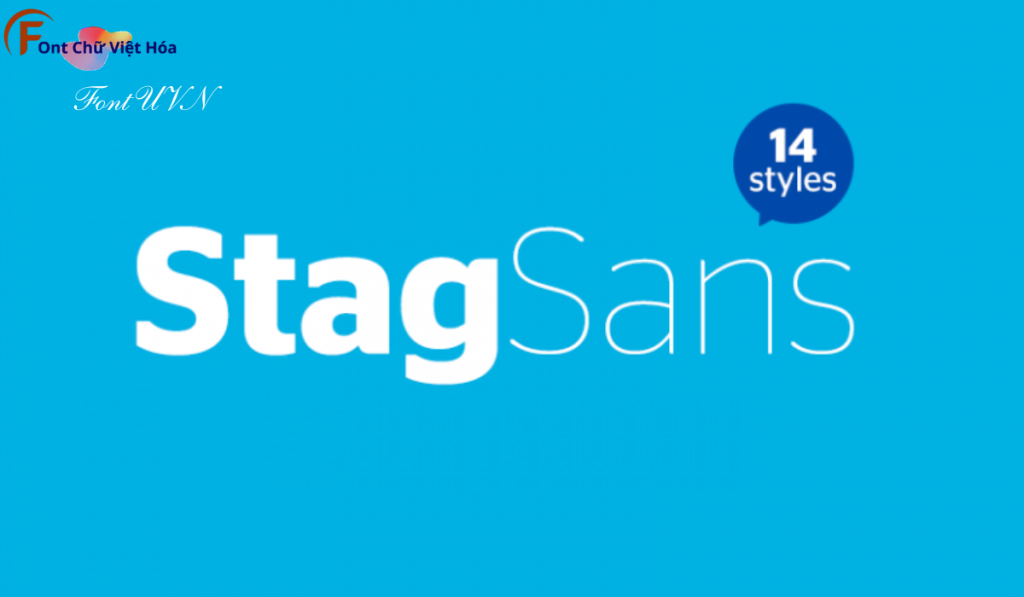
Font Continental Stag Sans UVN Việt Hóa
Tác giả: Continental Stag Sans
Bộ Font: UVN
Phân loại: Cá tính, Độc đáo
Độ dày: Thường
Font Continental Stag Sans UVN Việt Hóa là một font chữ không chân cá tính, thuộc bộ font UVN. Được thiết kế với mục tiêu mang lại sự độc đáo và sáng tạo, font này lý tưởng cho các dự án thiết kế như logo, poster, và bao bì sản phẩm. Với các nét chữ sắc nét và độ dày đều đặn, Font Continental Stag Sans UVN Việt Hóa không chỉ dễ đọc mà còn tạo cảm giác hiện đại và phá cách. Việc Việt hóa font giúp người dùng dễ dàng sử dụng trong các thiết kế tiếng Việt, mang lại sự tiện lợi và thẩm mỹ cao.